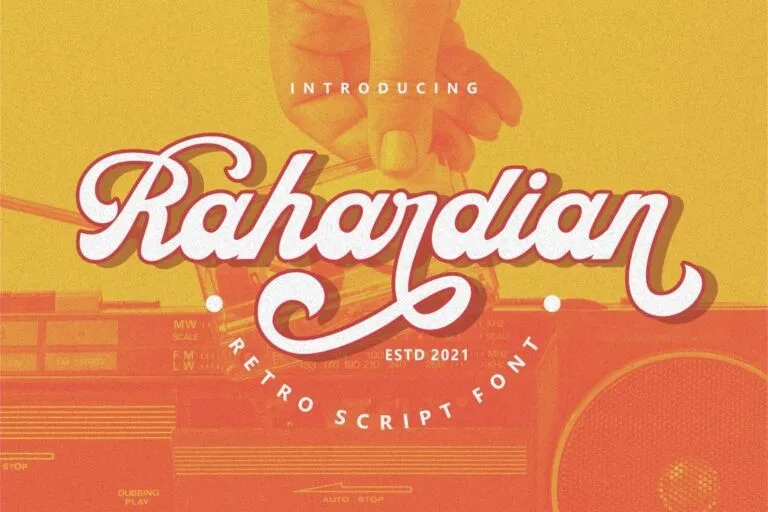
Rahardian Font – Download Grátis
A Rahardian é uma fonte script que oferece um estilo arrojado com visuais nobres e vintage. Esse tipo de letra possui muitas alternativas de caracteres, desenhos suaves (swashes) e ligaturas. Ideal para design retro e vintage, em estilos como logomarcas, camisetas, posters, marcas de empresa, embalagens, sinalização, capas de livros e muito mais. Se procura uma fonte que possa dar um toque único a qualquer projeto, seja ele digital ou impresso, a Rahardian é perfeita. Suas alternativas de caracteres oferecem liberdade para criar designs diferentes e acentuados, enquanto as ligaturas tornam suas aplicações mais sofisticadas e profissionais. Se você está buscando uma fonte que pode deixar seu projeto em evidência sem esforço algum, vale a pena experimentar a Rahardian. Essa fonte é sua chave para criar um design marcante no mundo das letras digitais ou impressas.